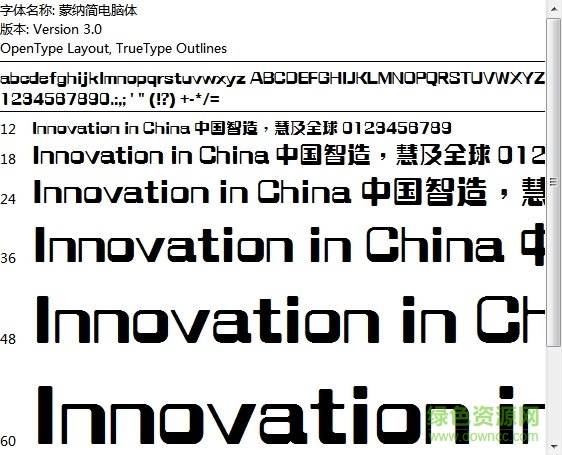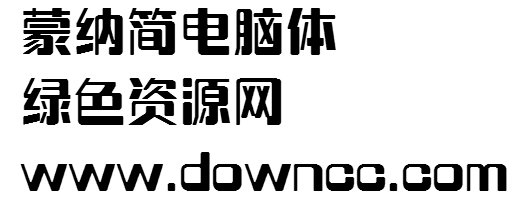
mcomputer hks bold蒙納簡電腦體
mcomputerhks字體,即蒙納簡電腦體,是蒙納字體庫中一款電子科技風格字體,采用不同的粗細設計,讓文字顯得十分立體,整體效果和諧而出彩,綠色資源網今日推薦!
蒙納簡電腦體特色
mcomputer hks bold字體,輸入繁體字,顯示簡體字,適合繁體字體用戶使用,簡體中文字庫不是很完整,需將其轉換為繁體問題方能使用!
mcomputer字體